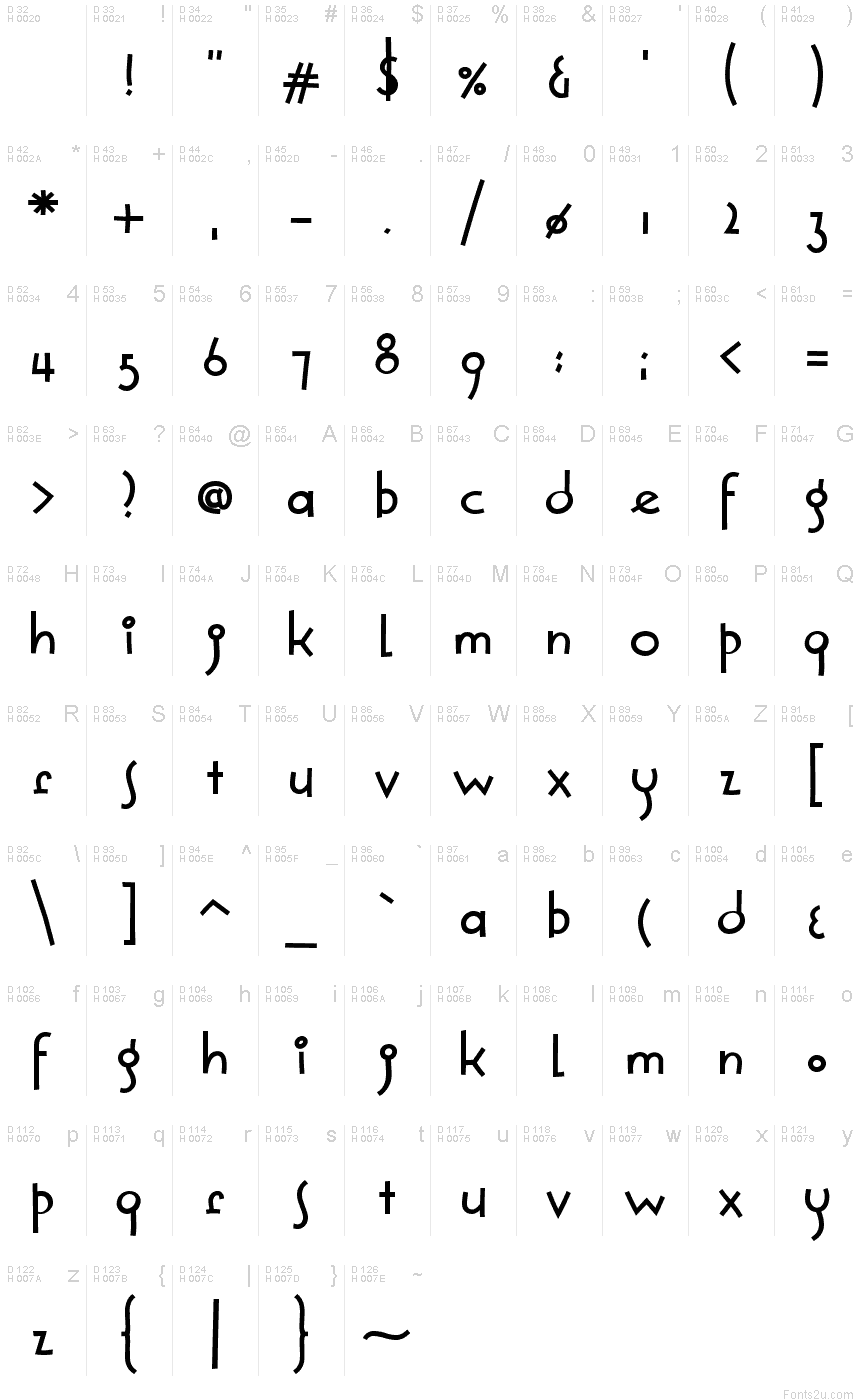
Solea-Bold 字体
Solea-Bold
Solea Bold 由 Francois Bruel 设计,是一款免费的新艺术风格 (Art Nouveau) 显示字体,节奏沉稳,极具海报感。字形融合了流畅的圆润线条、独特的锥形钩笔以及干练的垂直切割,呈现出一种早期现代主义的手绘质感,同时又不失图形设计的张力。
它非常适合精品店和咖啡馆的品牌设计、杂志标题、音乐海报、标题卡片以及包装设计,当简短的词汇需要独特的视觉轮廓而非平庸的修饰时,它就是理想之选。作为一款免费字体,Solea Bold 同样适用于制作字母组合、首字下沉和活动视觉识别,其弯曲的切口和挺拔的笔画,即使是寥寥数字,也能赋予文字鲜明的个性。